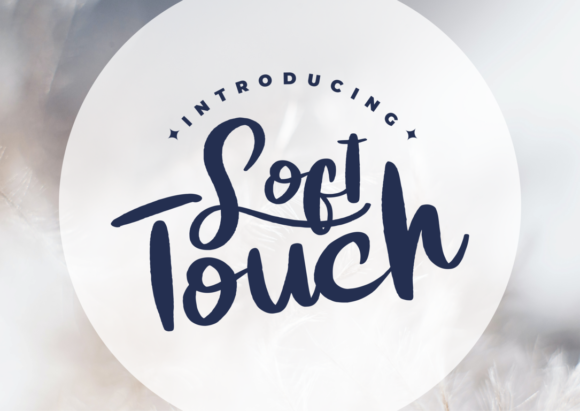
Soft Touch
Soft Touch : la police manuscrite polyvalente qui séduit les créateurs
Découvrez Soft Touch, une police d’écriture manuscrite à la fois détendue et ultra‑adaptable. Grâce à son encodage PUA, chaque glyphe et chaque swash sont accessibles en un clin d’œil, vous permettant d’enrichir vos projets sans aucune contrainte technique.
Pourquoi choisir Soft Touch pour vos créations ?
- Style manuscrit naturel qui apporte chaleur et authenticité à vos designs.
- Encodage PUA complet : accès immédiat à tous les caractères spéciaux, ligatures et ornements.
- Adaptabilité parfaite : idéale pour les logos, invitations, affiches, réseaux sociaux et bien plus.
- Résultat professionnel assuré : laissez-vous surprendre par la qualité du rendu final.